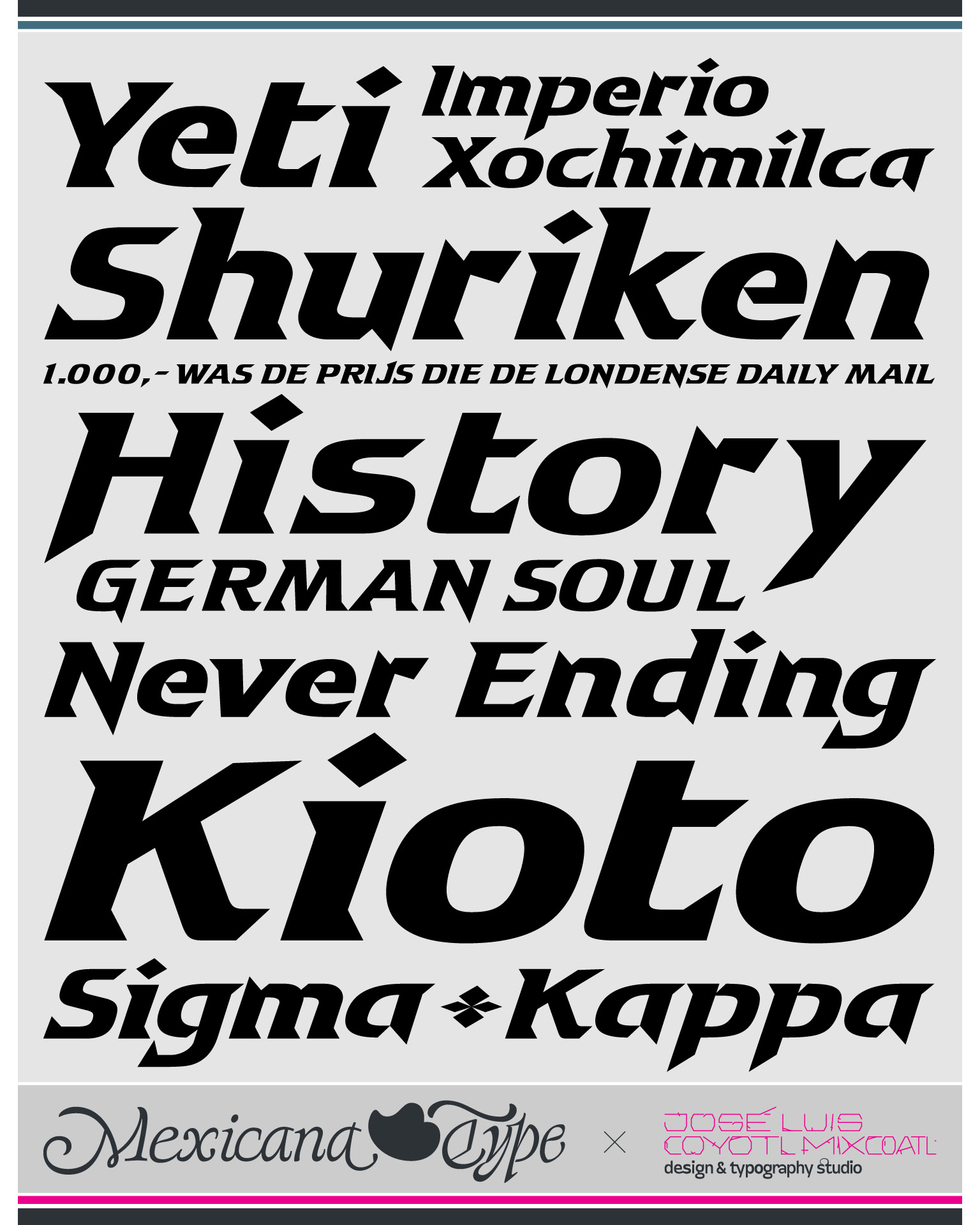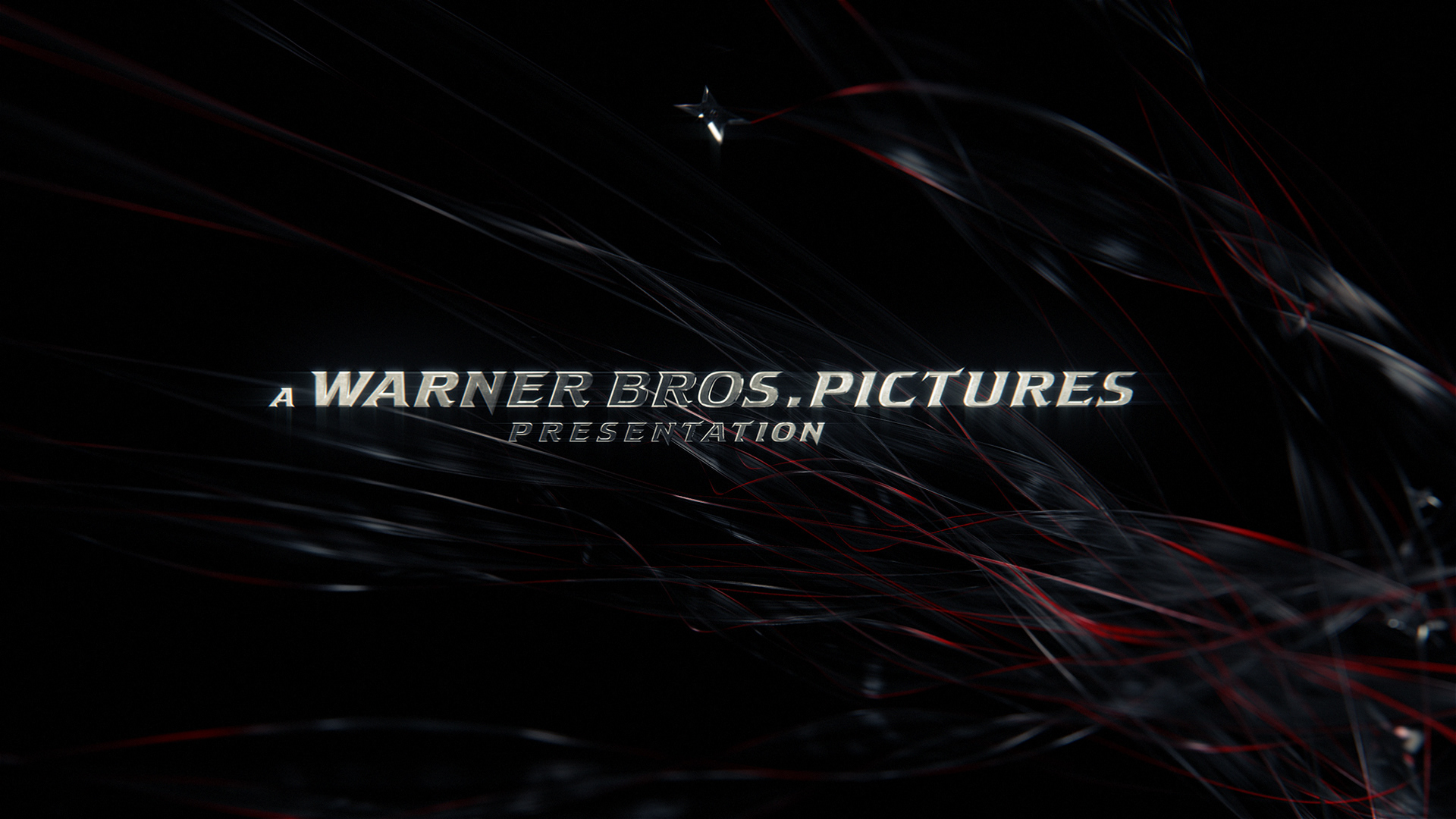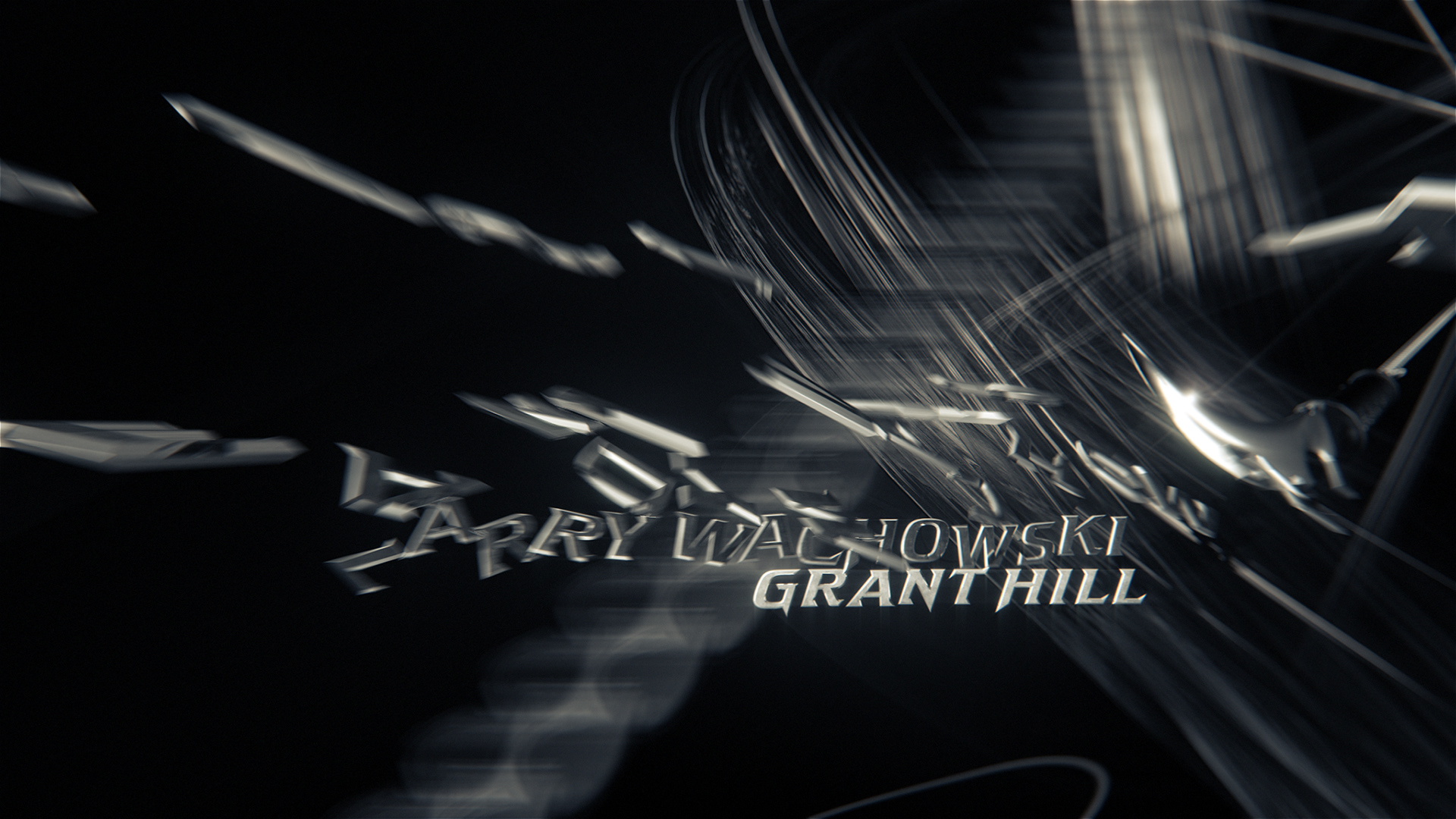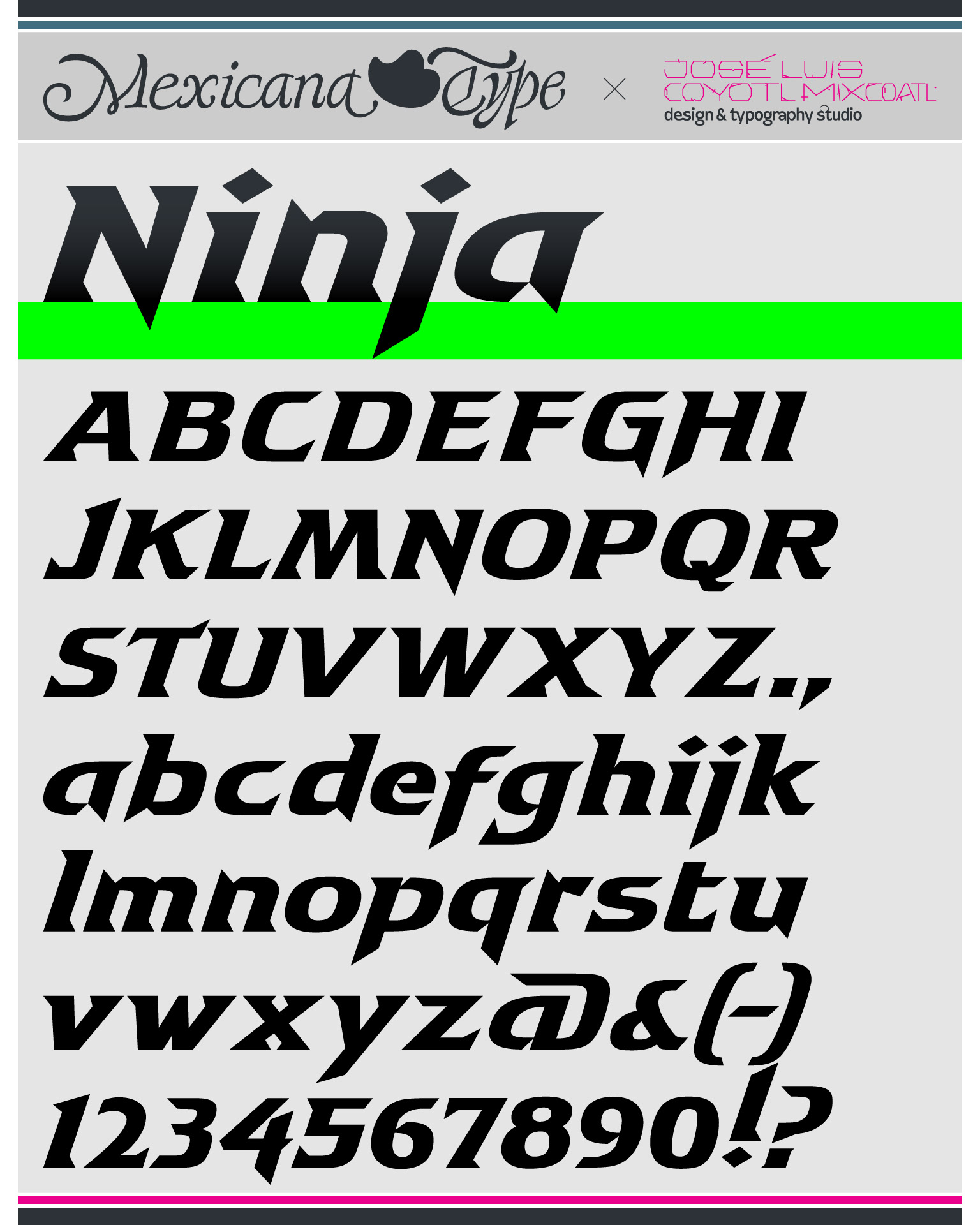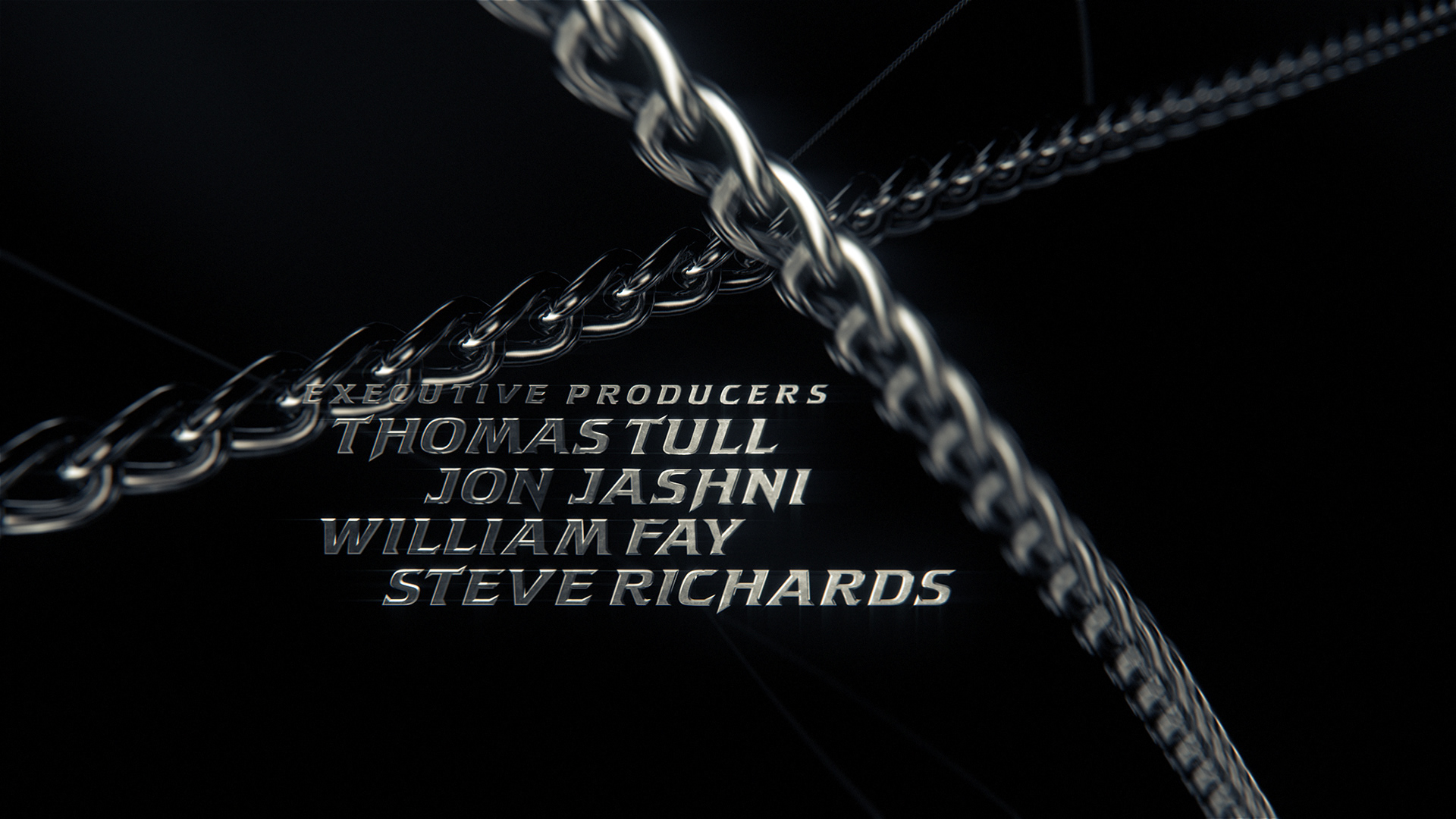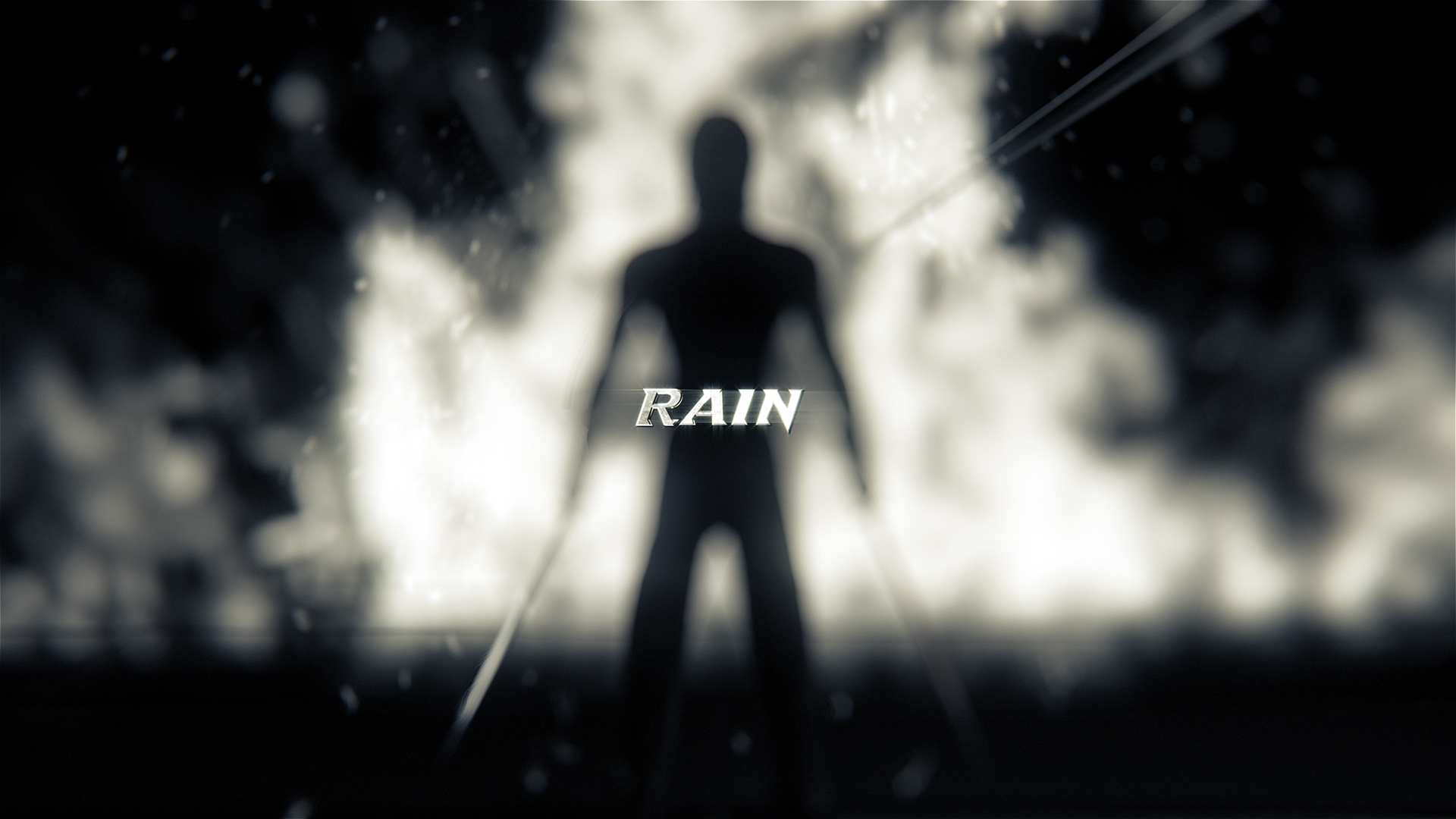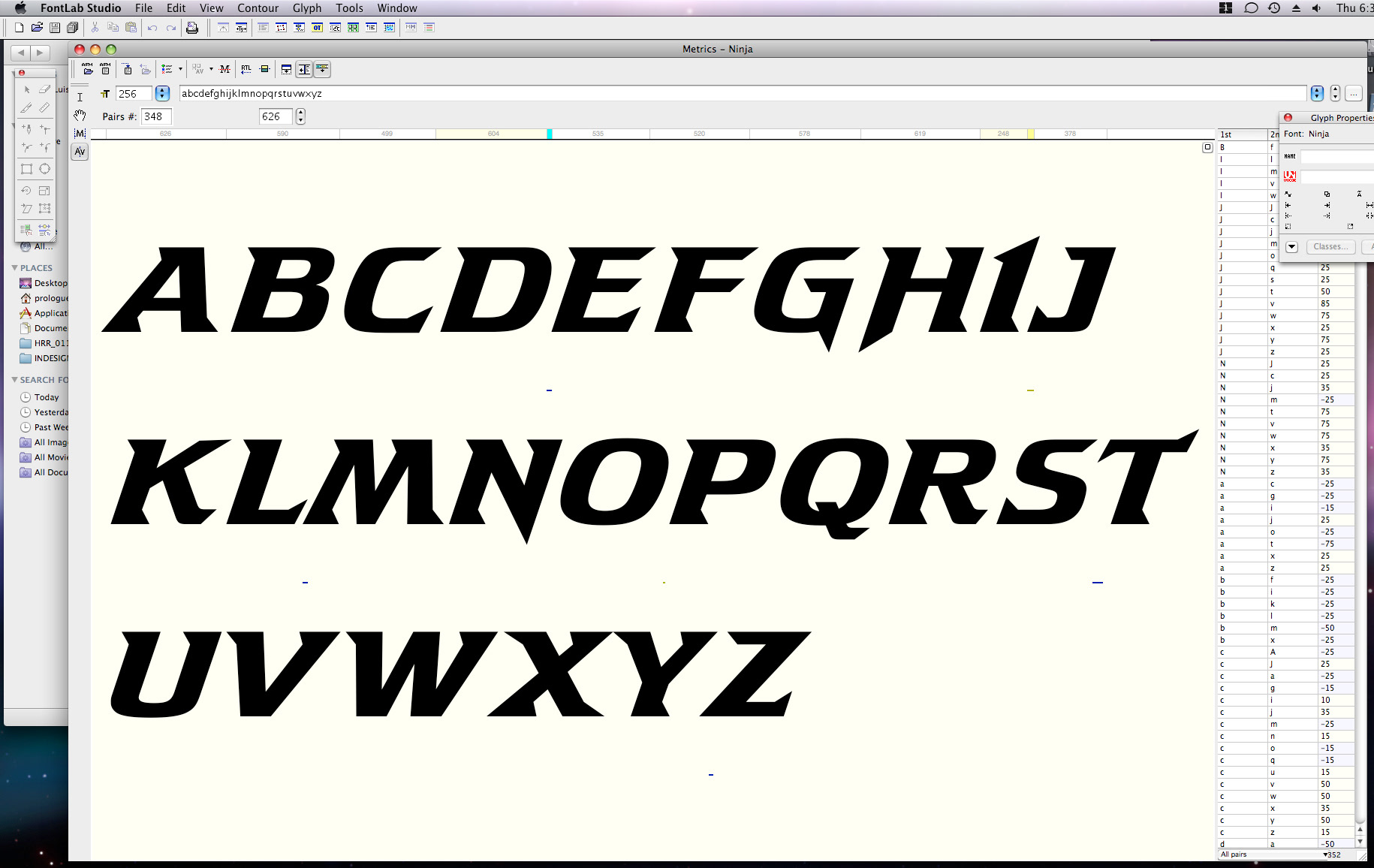
MxT Ninja fue diseñada para la secuencia de créditos finales de la película 'Ninja Assassin', dirigida por James McTeigue y producida por los Hermanos Wachowski. Fue concebida como custom type originalmente para los textos de la secuencia, una vez terminada el cliente solicitó la versión como fuente, lo que por supuesto no existía pues todo se había hecho desde el diagramado vectorial, de modo que se tuvo que hacer el archivo digital como custom font para necesidades de marketing, trailer, endcrawl, entre otros.
MxT Ninja parte de la necesidad de diseñar una fuente que se acoplara a la temática de este género de acción, policíaca y de escenas de combate con ninjas, y que se acoplatra a una secuencia de CGI ya probada por el cliente y en la que la parte que faltaba por definir era la de tipografía. De modo que se diseñaron caracteres en estilo itálico, con trazos y terminaciones con ángulos agudos a manera de armas punzocortantes. En la secuencia, las letras entraban a cuadro desplazándose como si volaran a traves del aire, se acoplaban en las lineas de texto y se deslizaban sobre su línea base y nuevamente salían de escena para que otras integraran las siguientes líneas de créditos, por ello es que inicialmente se diseñaron sólo mayúsculas/altas. Estas además en el modelado y render en 3D, tenían una textura de acero semipulido a rugoso con los bordes afilados, además en un entorno oscuro en el que las cámaras e iluminación contrastada también lanzaban destellos de partes pulidas y filosas, lo cual determinó el ancho de letra y el grosor de su trazo, así como el ángulo de su inclinación, además de la proporción de su alto para cuidar que la composición de textos estuviera dentro del rango de visualización y lectura de cada crédito. Esto también determinó el estilo de sus serifs, lo cual después también fue la base para la construcción de minúsculas y otros elementos tipográficos. De igual forma tendría que funcionar en colores sólidos y en tamaños reducidos. De la misma forma también sirvió para diseñar el título principal y otros elementos dentro del paquete de créditos de la película.